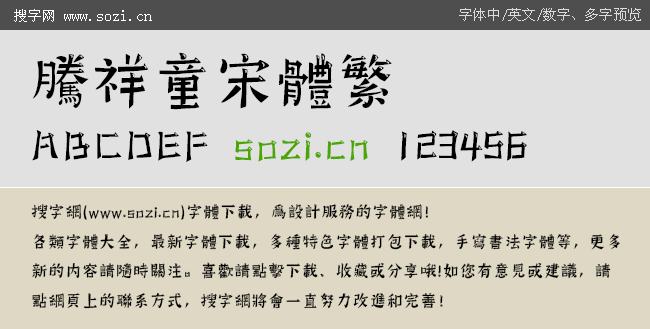
騰祥童宋體繁
搜字網(wǎng)提供一款騰祥童宋體繁中文藝術(shù)字體下載,該字體風(fēng)格鮮明、特點(diǎn)突出。筆畫(huà)舒展流暢,頓挫有秩;筆畫(huà)間相互呼應(yīng)且張弛有度;字面大小均勻,筆畫(huà)規(guī)范,整款字透顯出行書(shū)行筆特點(diǎn),然而又打破傳統(tǒng)書(shū)法概念運(yùn)用新的手寫(xiě)方法形成一款生機(jī)盎然、清新活潑的字體?捎糜谟∷⒊霭、包裝設(shè)計(jì)、廣告設(shè)計(jì)、網(wǎng)頁(yè)設(shè)計(jì)等。